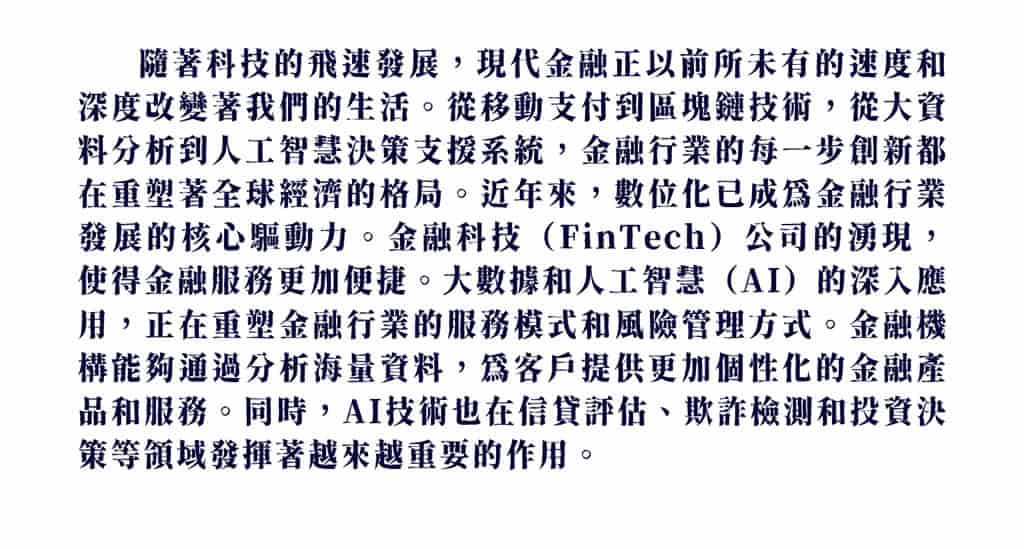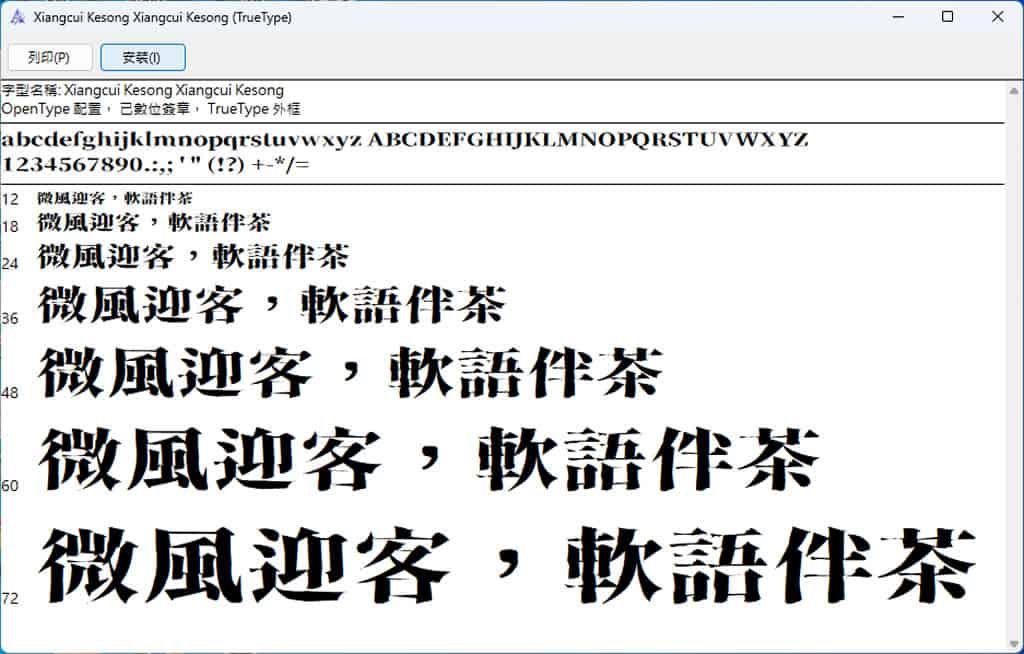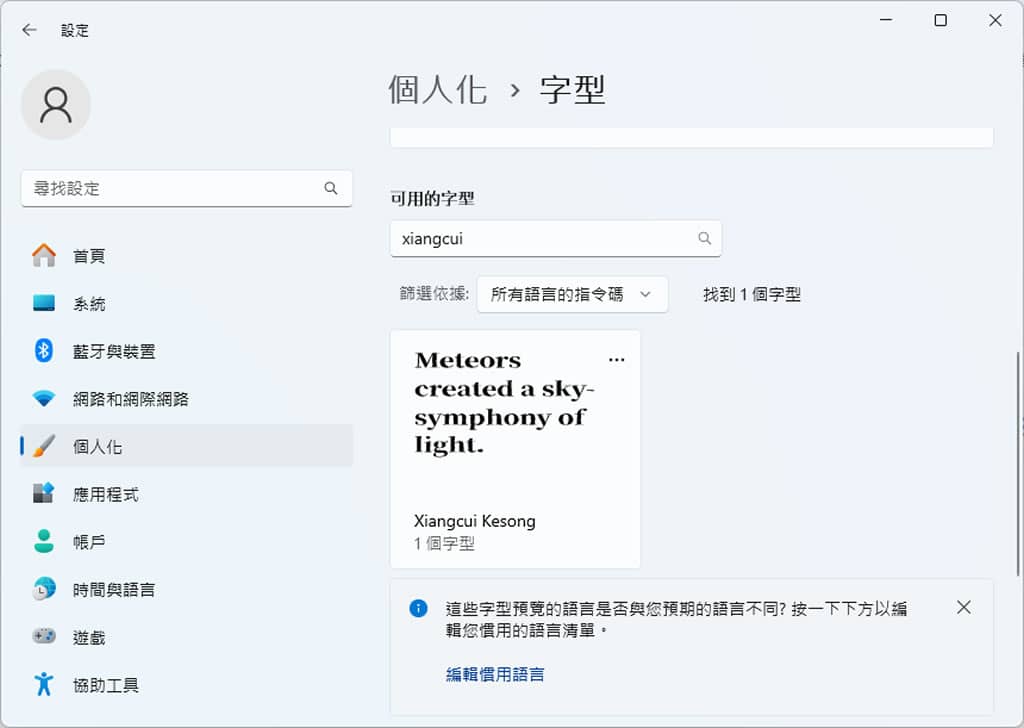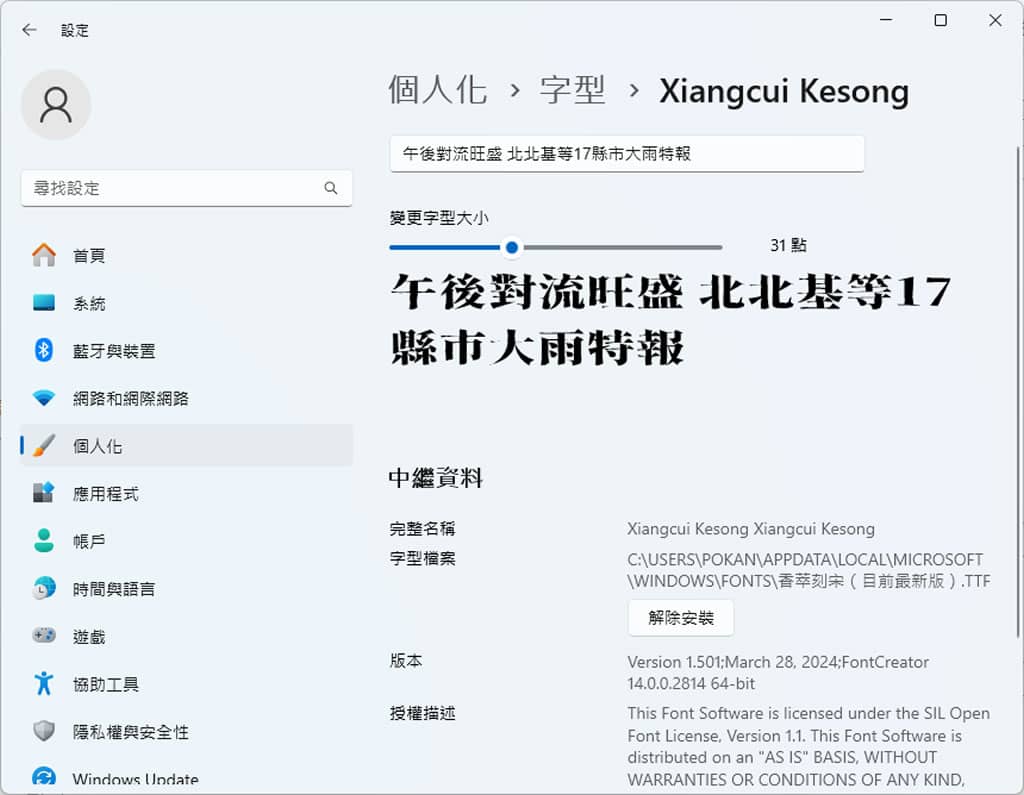
「香萃刻宋」是一款改造自開源思源系列的免費中文字型,支援繁體與簡體中文,無論是個人或商業用途皆可合法使用。此字體在設計上融合了雕刻宋體的古典筆意與現代視覺感,筆畫尖銳、結構精緻,帶有強烈的視覺衝擊力與復古氛圍,特別適合應用在標題設計、海報排版、懸疑風格遊戲、視聽作品等需要文化張力的場景。使用舊字形風格,也讓它在內文排印上同樣具備辨識度與閱讀性。
基於思源字體改造,支援繁簡中文與舊字型,適合設計、印刷與視聽創作